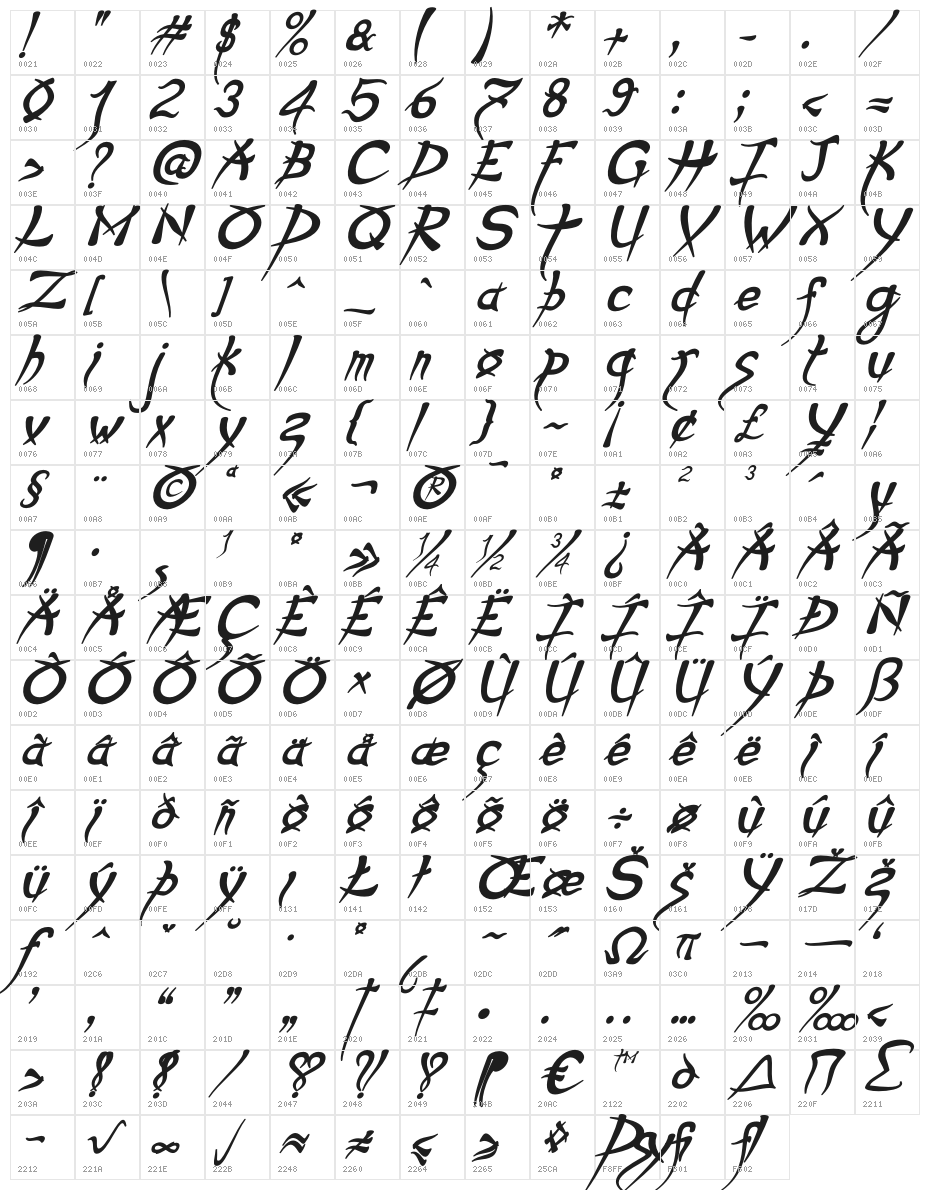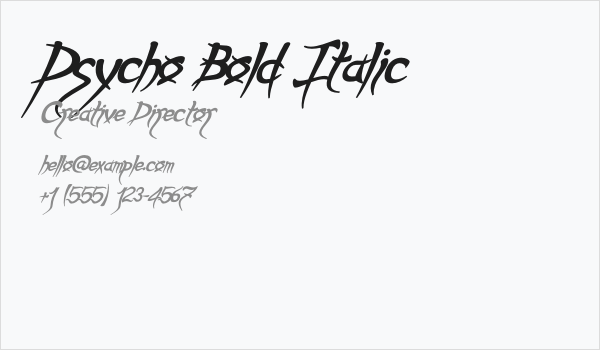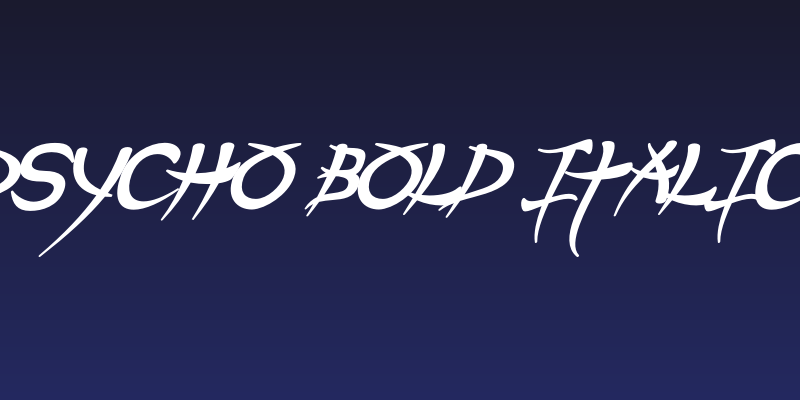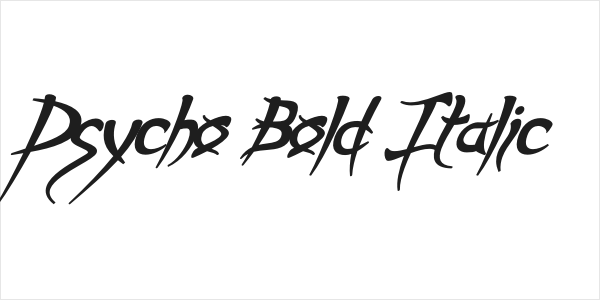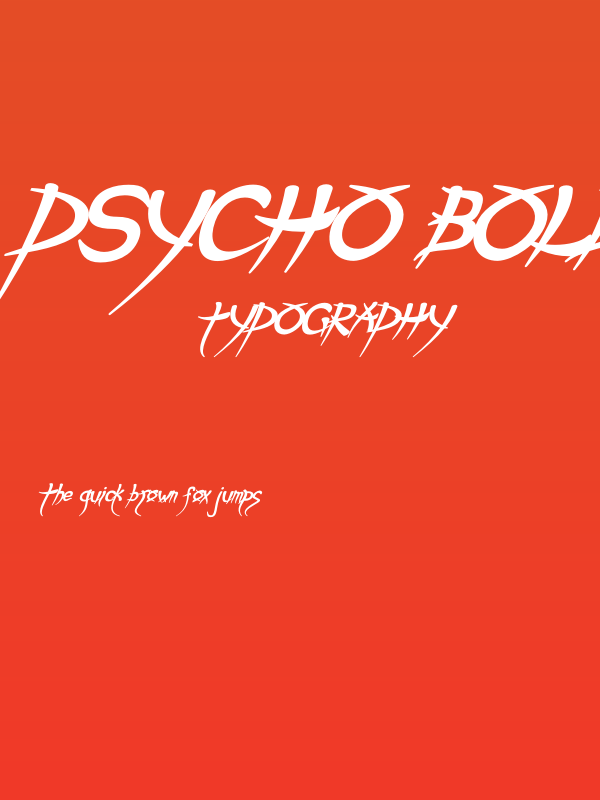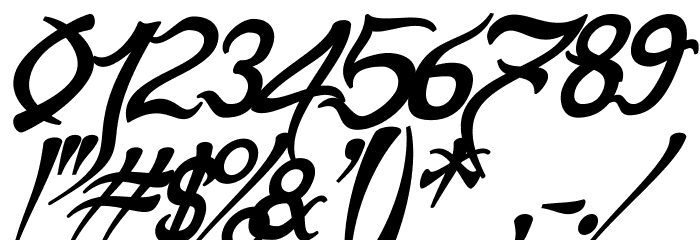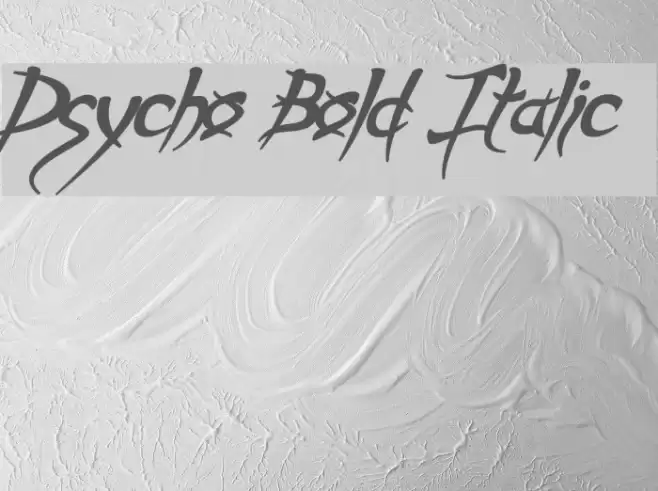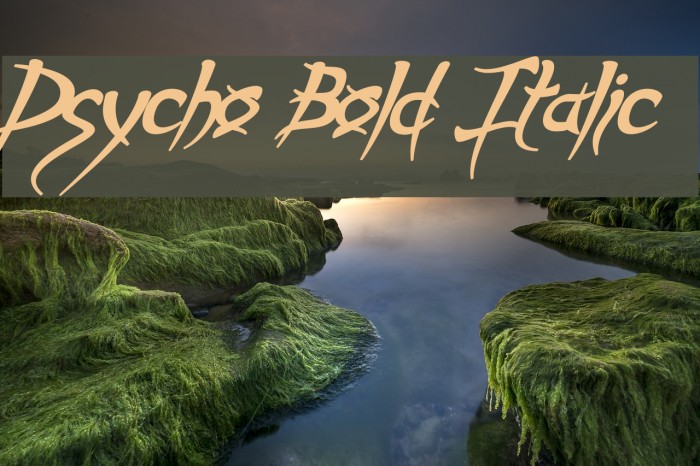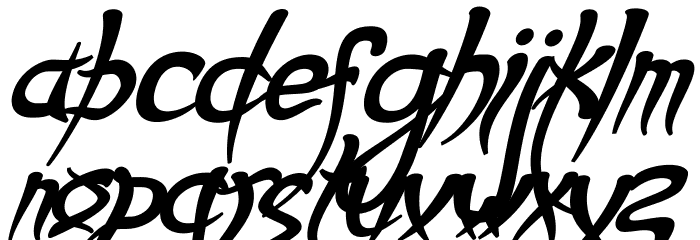
Psycho Bold Italic Font
| Style général | Modern, Energetic |
| Projets proposés | Ideal for edgy branding, music album covers, posters, and creative projects that require a bold statement. |